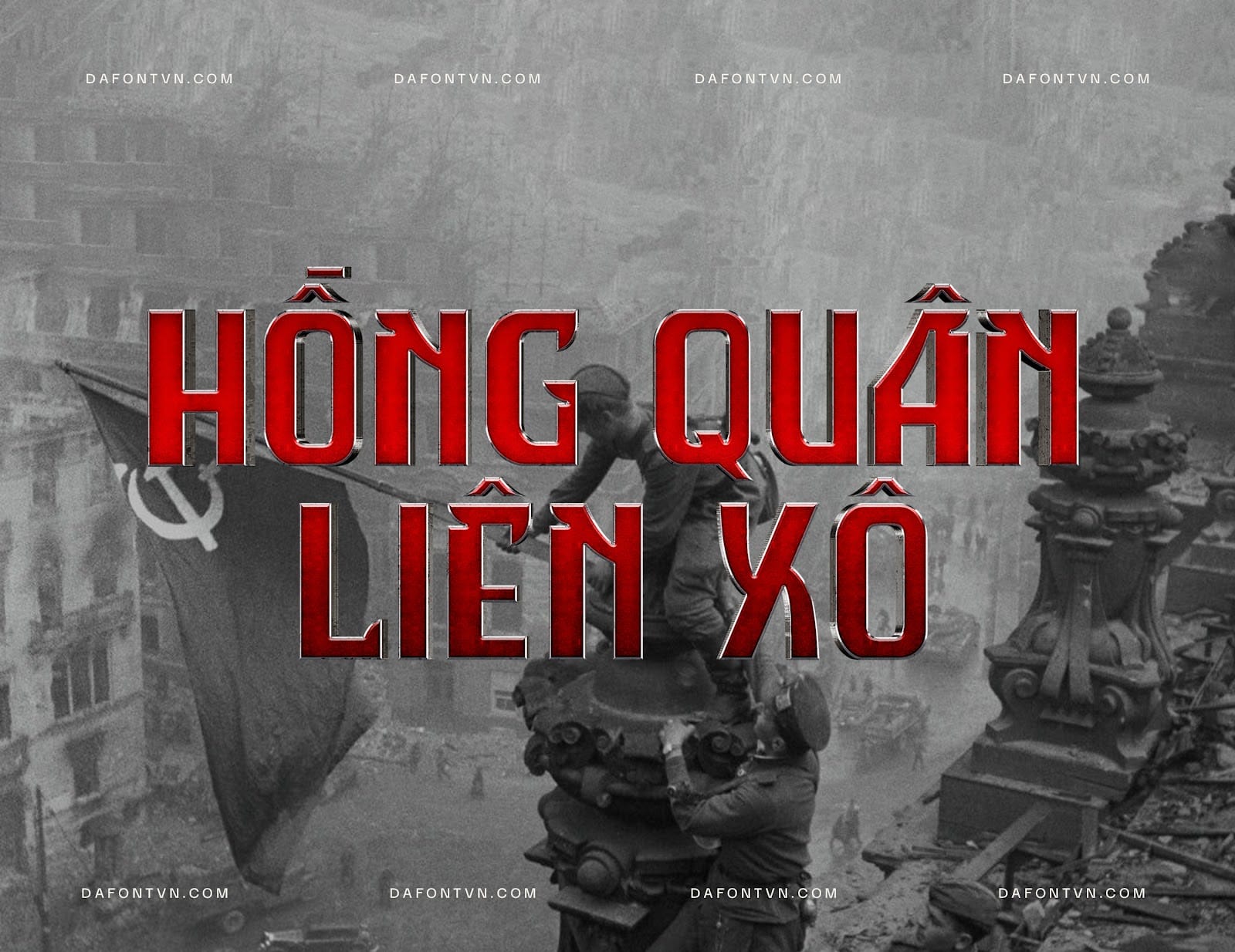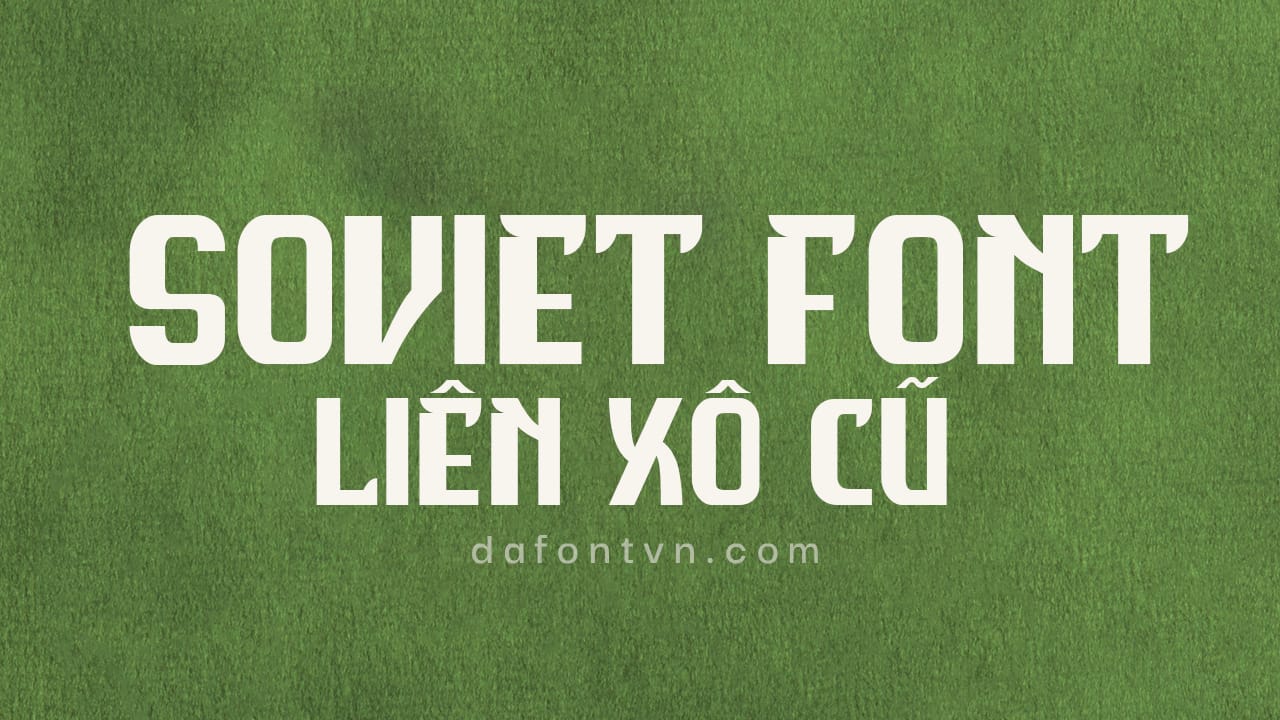
Soviet Font là một font chữ tiếng Việt được thiết kế bởi tác giả tonynguyen, font chữ được bắt nguồn từ việc nghiên cứu theo những con chữ từ thời Liên Xô cũ, dựa trên các nhìn của tác giả qua những thiết kế cũ thời xưa, những ký ức tuổi thơ.Là một font chữ San-Serif không chan, kiểu chữ SoViet sở hữu các đường nét cứng chắc, nhưng cũng có những góc cắt mềm mại. Bạn có thể sử dụng font chữ này cho nhiều các thiết kế như cho tiêu đề, các đoạn văn bản dài, bao bì, tạp chí, quảng cáo…